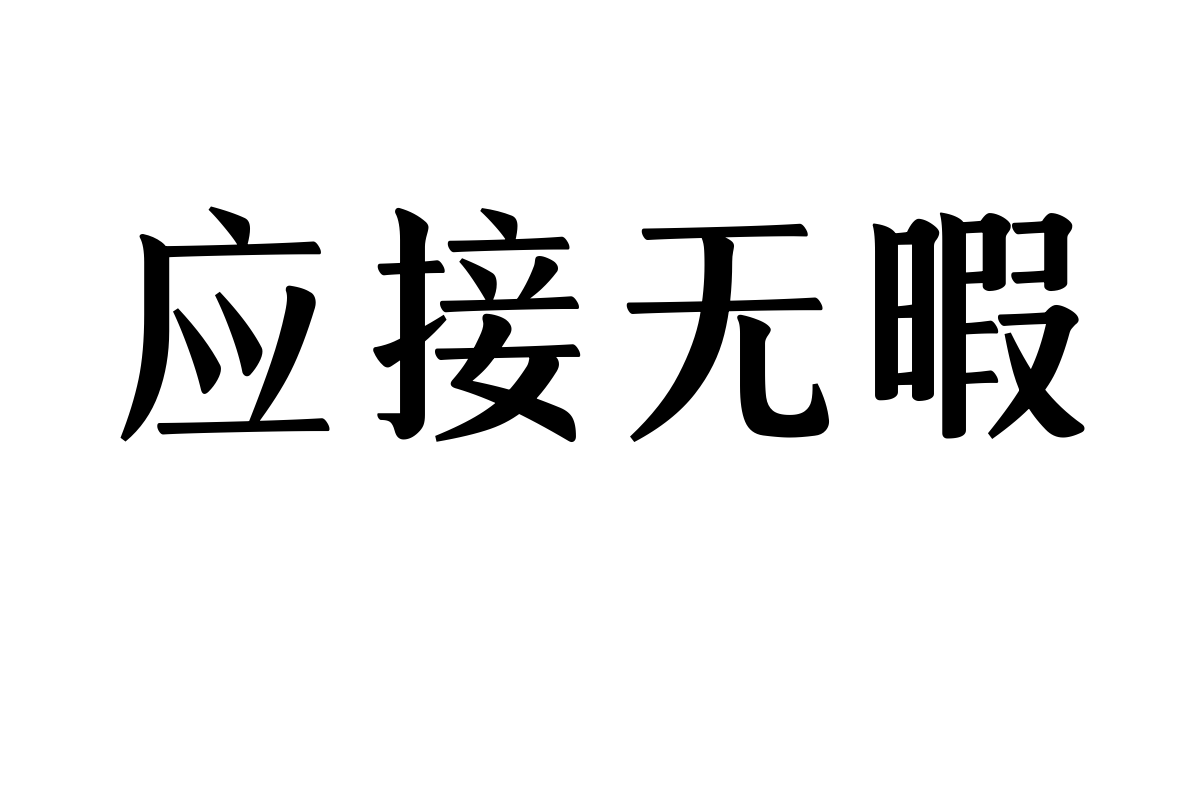
文道落花楷宋是一套由文道公司推出的中文字体,主要用于设计海报、书籍、广告等。这套字体的特点是笔画流畅,字形优美,具有很高的辨识度。它的笔画粗细适中,既有力度又不失柔美,给人一种优雅的感觉。同时,这套字体的字形结构严谨,线条分明,具有很强的视觉冲击力。总的来说,文道落花楷宋是一款非常适合用于设计海报、书籍、广告等场合的字体。